すごいぞ、さか立ちする文字! アンビグラム暗号のなぞ
KADOKAWAからアンビグラム作家・ノムラ イッセイ氏著書、フルカワマモる氏イラストによる「すごいぞ、さか立ちする文字! アンビグラム暗号のなぞ」が2019年2月14日から発売された。
ノムラ イッセイProfile●1990年生まれ。富山大学芸術文化学部卒。卒業後美術の臨時講師として小中高に勤務。映画「天使と悪魔」からアンビグラムに興味を持ち、その法則を独自に発展させ数々の作品を発表。現在はアンビグラム作家として広告や中学校美術の教科書にも起用されている。‘18年1月の競艇ポスター「挑戦(勝利)」はマスコミにも大きく取り上げられた。
「平成」をひっかり返すと「令和」になるという野村一晟(ノムラ イッセイ)氏のアンビグラム作品が話題になっているので、各書体で平成を普通にひっくり返すと令和になるか検証してみた
普通にひっくり返すだけでは、当然、令和にならなかったわ…。
平成をひっかり返すと令和になるという野村一晟氏のTWITTERでのアンビグラム作品を見てもらえれば分かるが、割とクセの強い、いやオオクセなハネやハライを使用しているので、単純にひっくり返すだけでは無理だったわ。
書体をひっくり返すのは諦めて、無理やり作ってみたわ。
アンビグラム
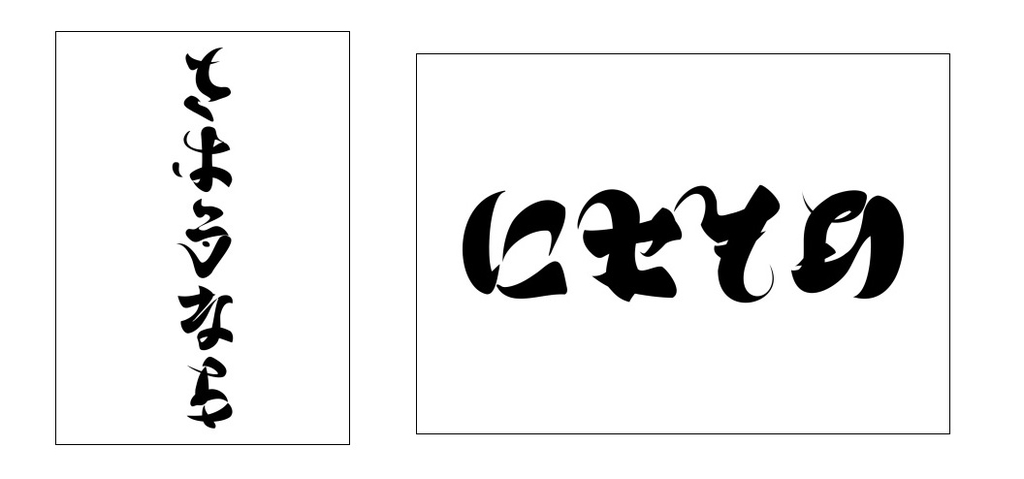
アンビグラムとは逆さにしたり鏡に映したりしても読める、意味も逆になったり別の意味になったりする、不思議な文字アートのこと。「アンビ(ambi)」は「両方の」、「グラム(gram)」は「文字」という意味。
言葉の裏の意味を表現できることが楽しいアンビグラムは、人の名前や、言葉に、大切なメッセージを込めることができる、脳トレや趣味など無限の可能性を持った言葉といえる。
頭も使って勉強にも役立つ、オールカラーのコミックやイラストがいっぱい!「すごいぞ、さか立ちする文字! アンビグラム暗号のなぞ」
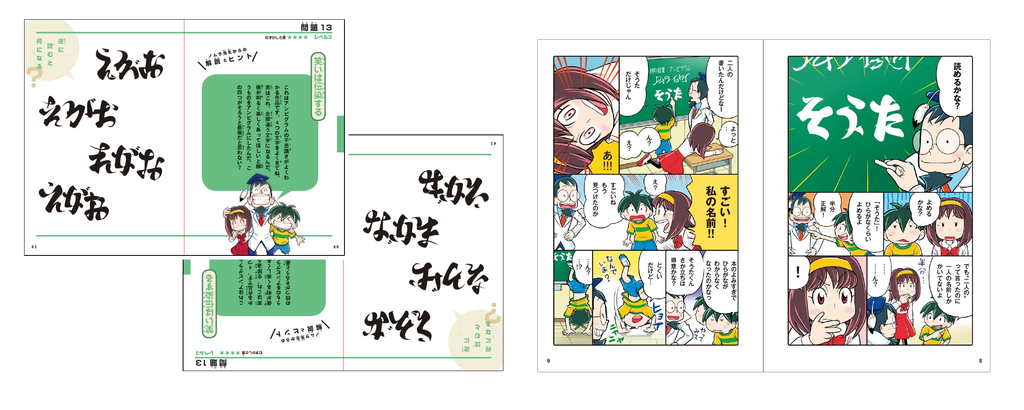
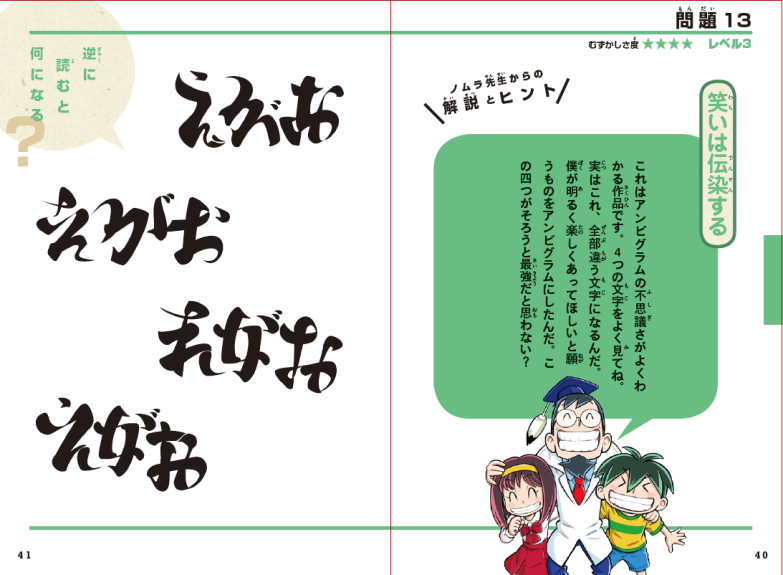
君には解けるかな? 逆さにするとなんと読める?
小学校の教室でそうたとまさみはノムラ先生からフシギな言葉を見せられる。
「アンビグラム」?
それは逆さにしても読めるフシギ文字。しかも意味が変わっちゃう?
例えばこれ、 逆さにするとなんと読めるかな?
キミはこの暗号が解けるか? メディアでも大きく話題の「アンビグラム」
小学校の教室でそうたとまさみはノムラ先生からフシギな言葉を見せられる。「アンビグラム」? 「アンビグラム」とは逆さにしても読めたり別の言葉になるフシギな文字アートのこと。例えば「さつまいも」、逆さにすると……、えー!なんでそうなるの? 自分の目が信じられなくなる、フシギがいっぱい、暗号いっぱい! 頭も使って勉強にも役立つ、オールカラーのコミックやイラストでとっても見やすい。テレビのクイズ番組で問題になったりして、話題の「アンビグラム」。本を逆さにしても読めるから、学校で友だちと机を挟んでクイズ合戦ができる! 脳トレにも役立つ無限の可能性を持った言葉が、どんな風に読めるか文字通り「頭をひねって」楽しんで!
ノムライッセイ(野村一晟)氏著書「つくろうよ! アンビグラム」
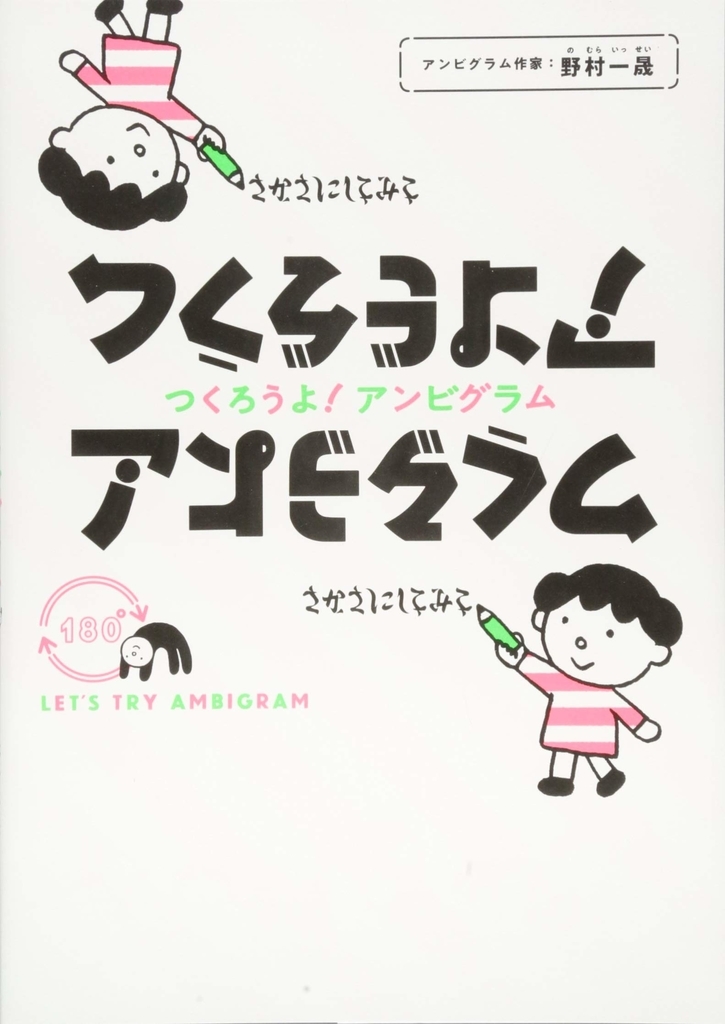
アンビグラム作家・ノムライッセイ(野村一晟)氏著書による、アンビグラムが書けるようになる「つくろうよ! アンビグラム」は飛鳥新社から2018年11月7日に発売された。
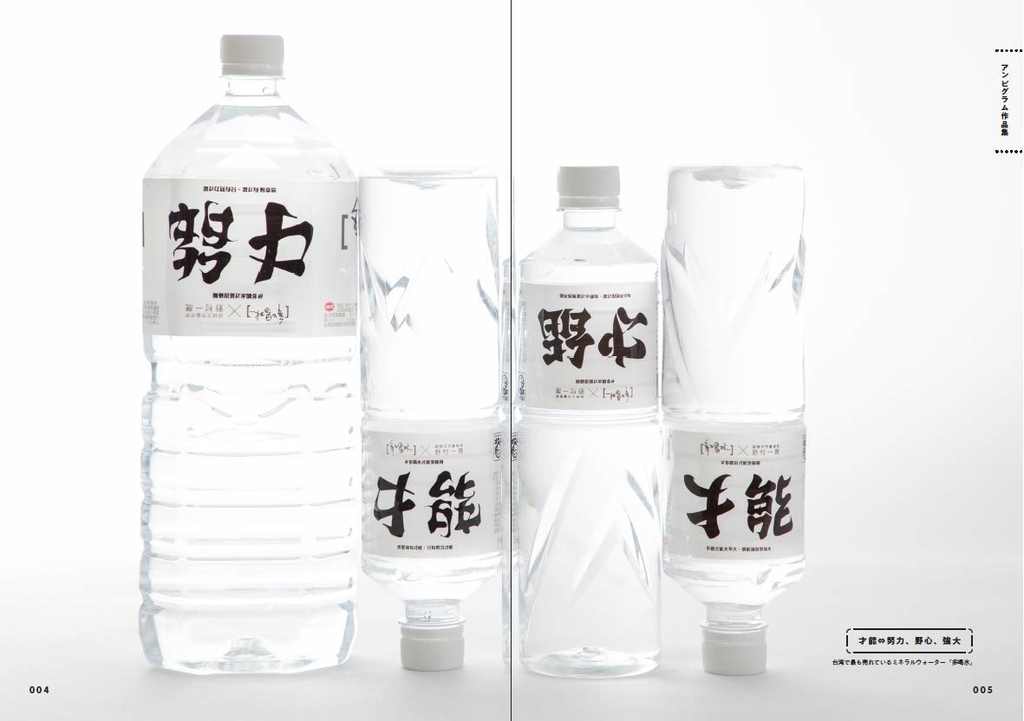
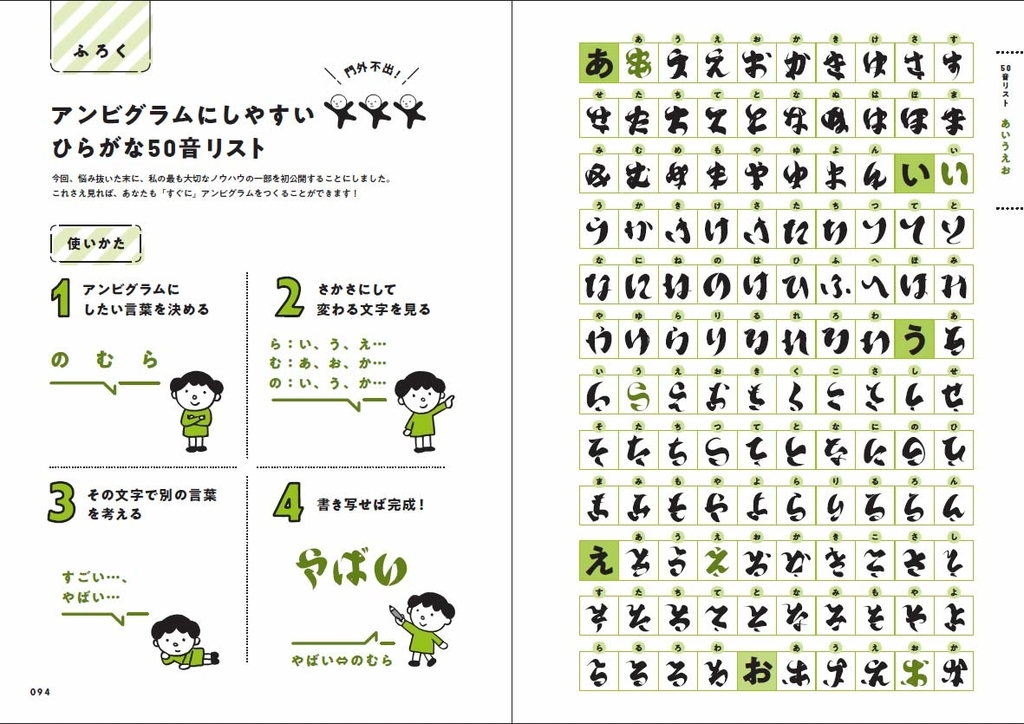
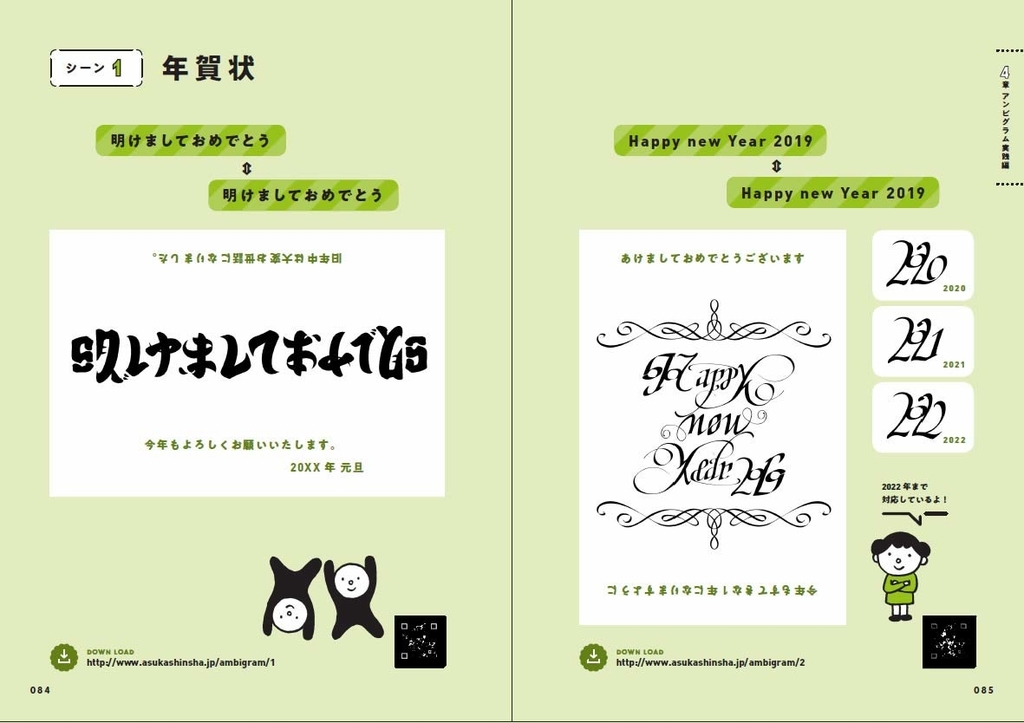
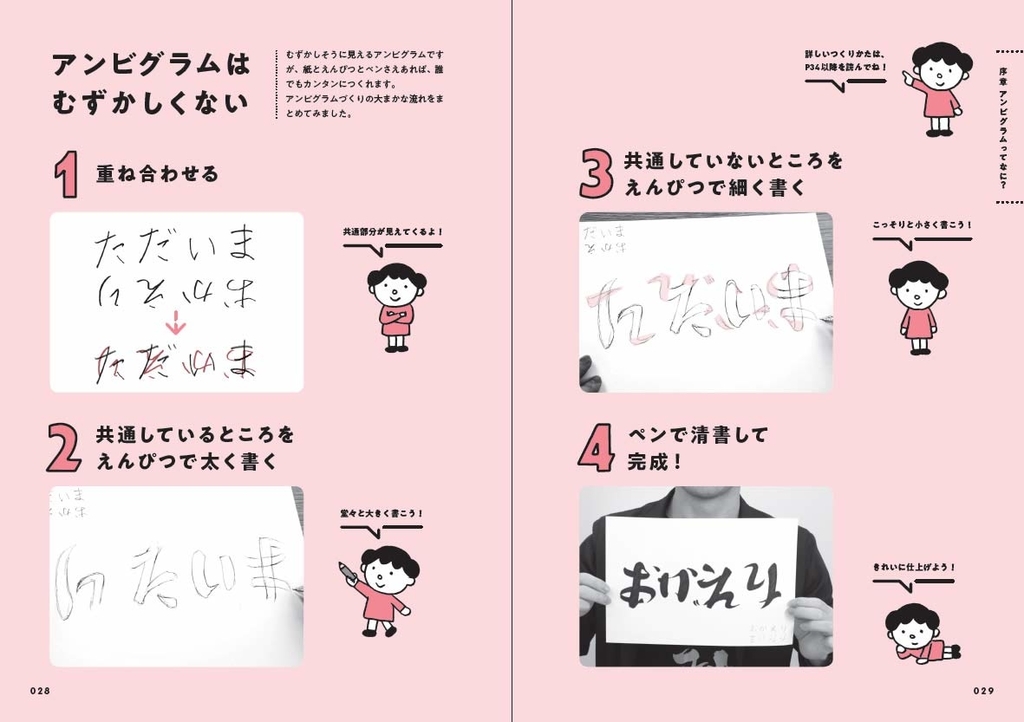
テレビで話題の、さかさで読める不思議文字「アンビグラム」。
そのアンビグラムが書けるようになる、まったく新しい本が誕生しました。
2大ふろくを収録!
1.もらってびっくり、「アンビグラム年賀状」4パターン
2.驚異の「アンビグラムひらがな50音リスト」 (「あ⇔あ」「い⇔は」など、各文字に対応! )
(あなたも「すぐに」アンビグラムがつくれる! )
アンビグラムは、楽しくて役に立つ!
脳トレ、自由研究、アート制作に!
年賀状、メッセージカード、名刺に!
あなたも、アンビグラムをつくってみませんか?
いま、アンビグラムのブームが来ています!
著者のアンビグラム作品がツイッターで10万回以上リツイート!
●アンビグラム作品集
●アンビグラムとは
●序章 アンビグラムってなに?
さかさにしても読めるのはなぜ?
脳の習性を逆手にとる
視線の動きを逆手にとる
アンビグラムはむずかしくない
こんなにたくさん! アンビグラムの使いみち
COLUMN 人生を変えるアンビグラム1
新婚カップルをよりラブラブに
●1章 アンビグラム基礎編
アンビグラムは2種類ある!
<さかさにすると同じ言葉になるもの>
STEP1 同じ言葉を上下に並べて、重ね合わせる
STEP2 共通しているところをえんぴつで太く書く
STEP3 共通していないところをえんぴつで細く付け足す
STEP4 えんぴつの下書きをペンでふち取りする
STEP5 紙に転写し、回転させて、再度転写すれば完成
<さかさにすると違う言葉になるもの>
STEP1 さかさにする言葉の候補を探す
STEP2 候補の文字を重ね合わせて検討する
STEP3 えんぴつで共通点を太く、共通しないところを細く書く
STEP4 えんぴつの下書きをペンで清書する
練習してみよう!
COLUMN 人生を変えるアンビグラム2
アンビグラムのポスターで売上が6億円もアップ!
●2章 アンビグラム技術編
法則1 仲間探しの法則
法則2 共通太めの法則
法則3 中間の法則
法則4 竜頭蛇尾の法則
法則5 分離統合の法則
法則6 同文字手間半分の法則
練習してみよう!
●3章 アンビグラム練習編
問題の解き方とコツ
Lv1問題
Lv2問題
Lv3問題
Lv4問題
Lv5問題
なぞってみよう!
●4章 アンビグラム実践編
思いを伝える! アンビグラム・メッセージカードのつくりかた
シーン1 年賀状で新年のご挨拶に
シーン2 お誕生日に
シーン3 お祝いに
シーン4 プレゼントに
シーン5 送別会に
●付録 門外不出! アンビグラムしやすいひらがな50音リスト